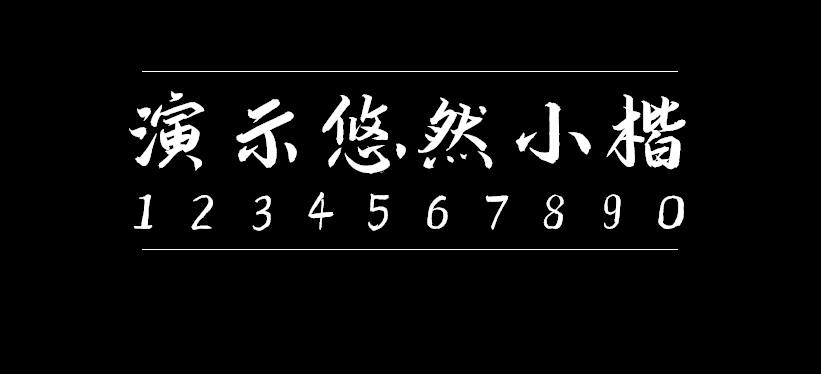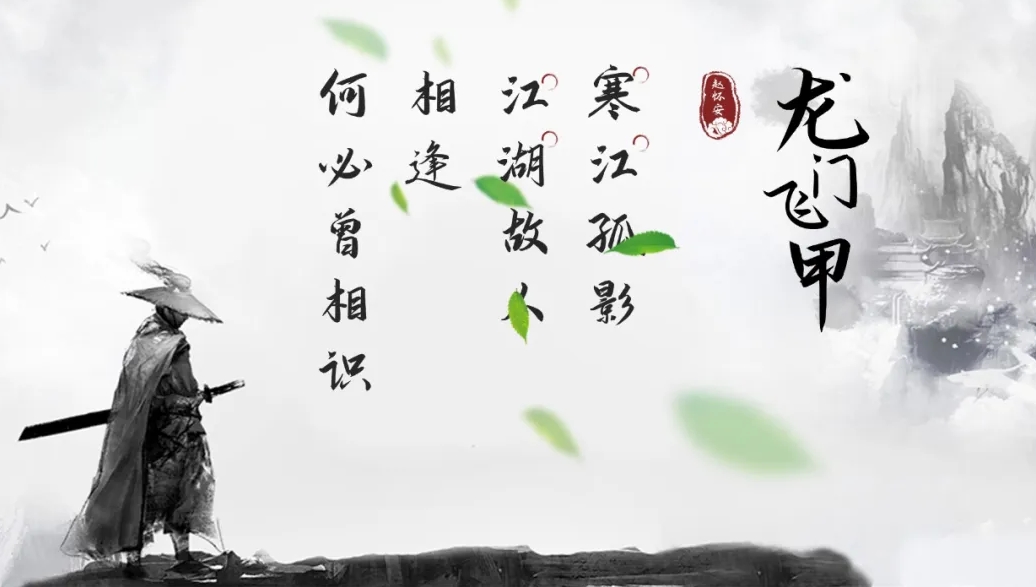
演示悠然小楷
演示悠然小楷是秋叶联合keynote研究所推出的一款书法字体,字稿的作者是孟祥媛,一位还在大学读书的书法专业学生。
初看「演示悠然小楷」,可能并不觉得惊艳,再品,却会发现透着质朴、率真的气息。正如尚在象牙塔中的作者本人,那是未经雕琢的拙朴书生气。接下来,一起体会悠然小楷的这股「拙气」。
悠然小楷笔画分明,结构清晰,没有过度的连笔和飞白,对阅读识别更为友好;小楷字形较小,天然拥有更大的字间距,即便作为长段文字使用,阅读上也不会有太大视觉压力;
悠然小楷的笔画力度分布均衡,起收有序,没有太过强烈的对比,自然沉劲而不漂浮;在小楷的基础上有些行楷的影子,为字体增添了灵动,但又有克制,形成停而不断、笔断意连之态;部分笔画细节可能并不完美,不够顺滑,但这份未经雕琢,又何尝不是一种难得的拙朴;
所以见过很多大开大合的书法字体后,再见悠然小楷,可能没有很惊艳之感。但艳丽与喧嚣并不一定代表力量,沉劲入骨更难能可贵。